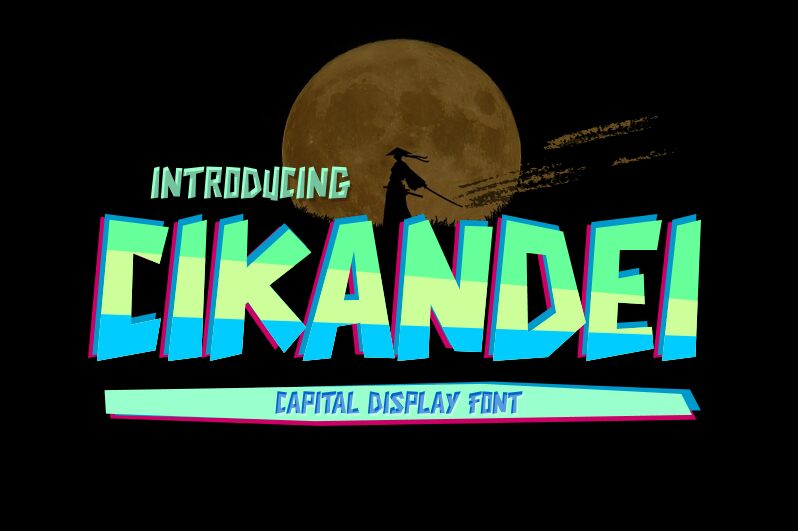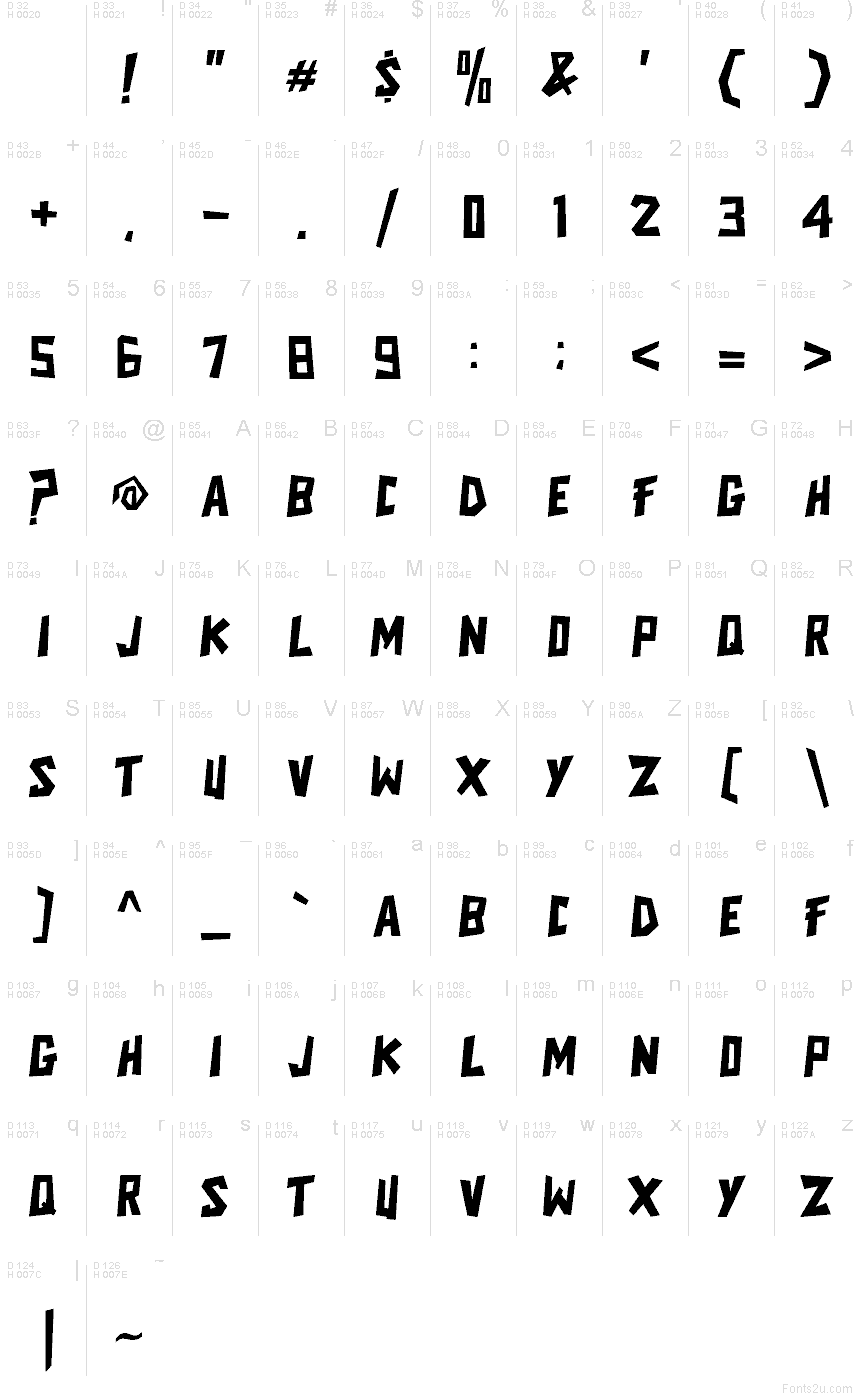
Cikandei, créé par Cikandei du Mabhal Studio, est une police d'affichage gratuite au style cartoon, dotée de majuscules massives aux coupes nettes et d'une allure vive, comme dessinée à la main. Les angles irréguliers, l'espacement serré et les formes en coin confèrent aux lettres l'impact du lettrage de bande dessinée, tout en conservant une silhouette audacieuse et directe.
Cette police gratuite est idéale pour les couvertures de BD, les logos de jeux, les emballages de snacks, les affiches d'événements et les articles dérivés ludiques. Ses formes compactes sont particulièrement efficaces pour les titres et les cartons de présentation, où ses bords inclinés et son rythme irrégulier suffisent à porter la composition sans avoir besoin d'ornements supplémentaires.